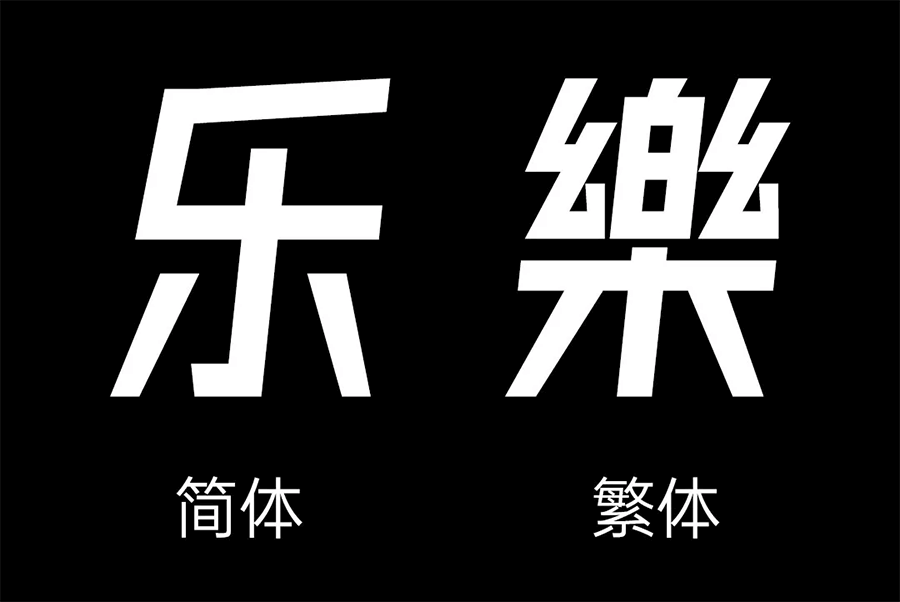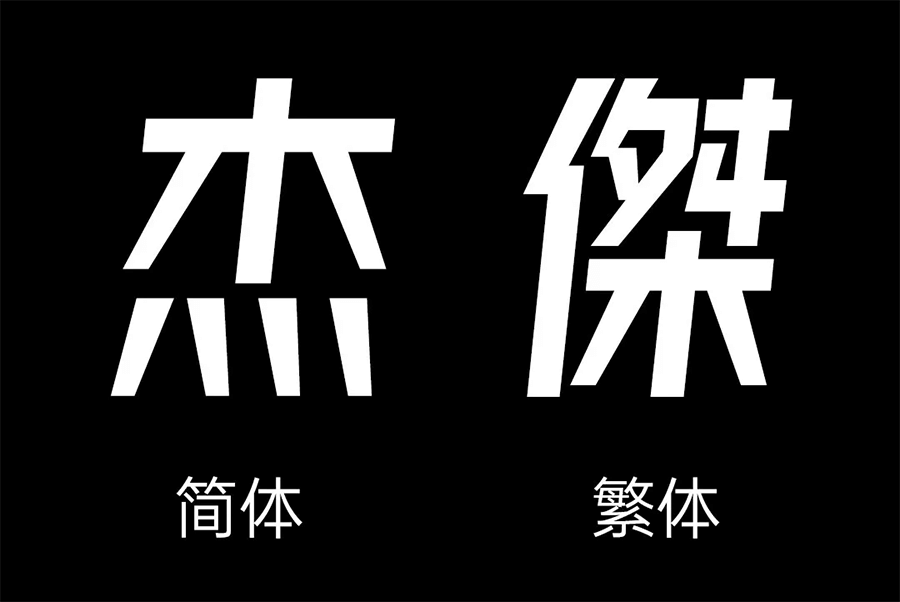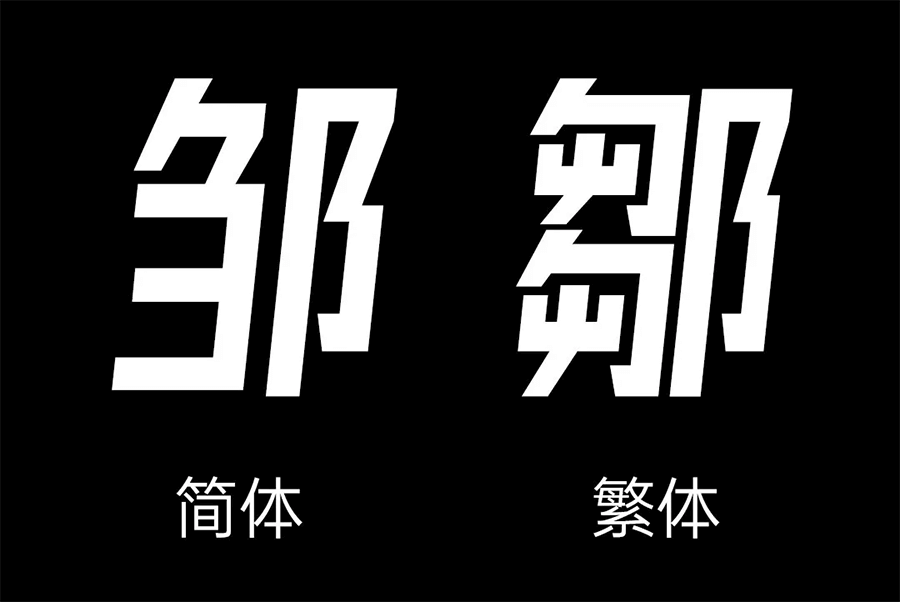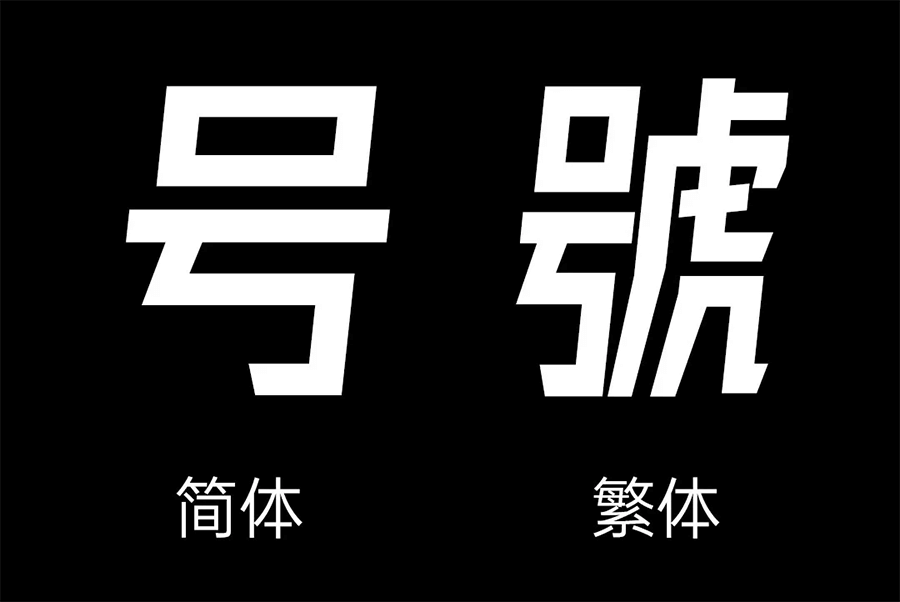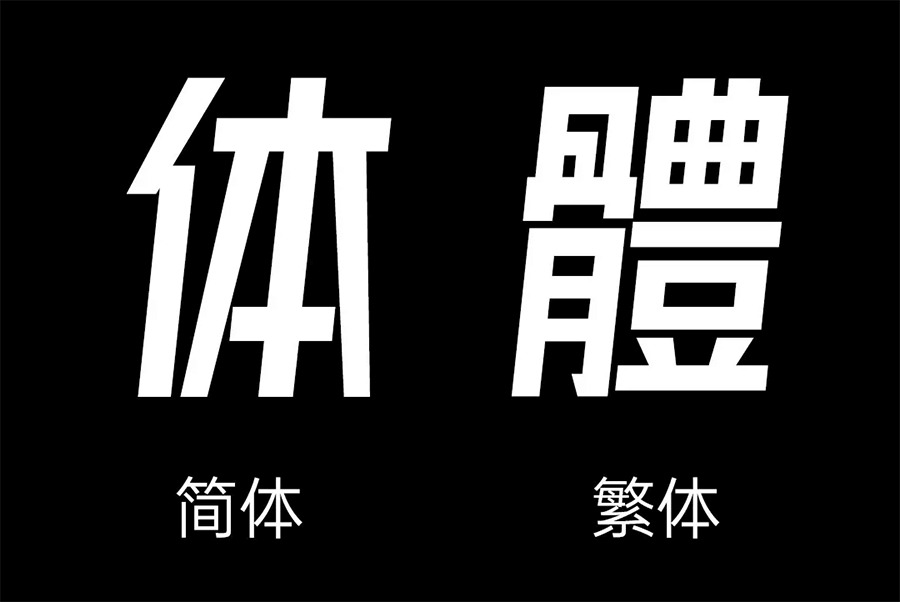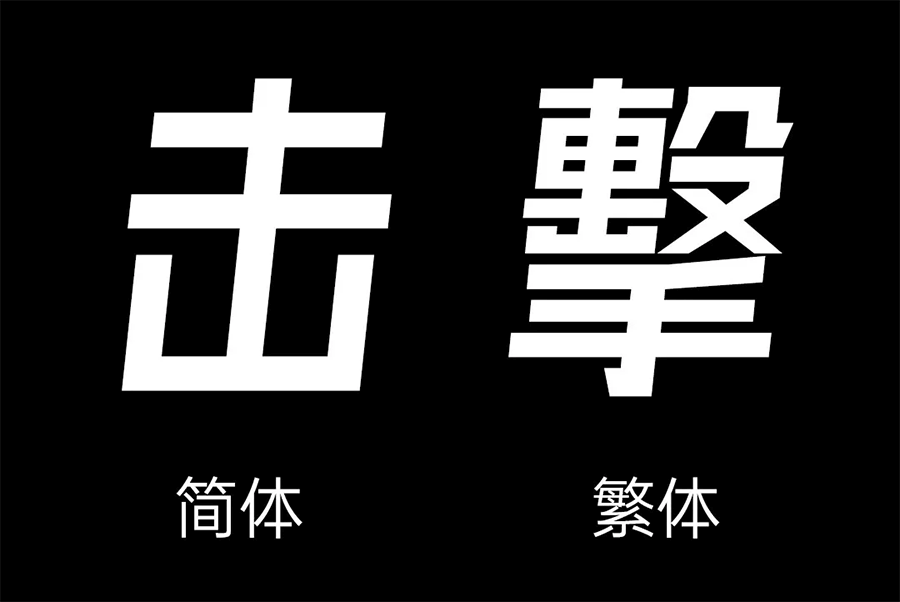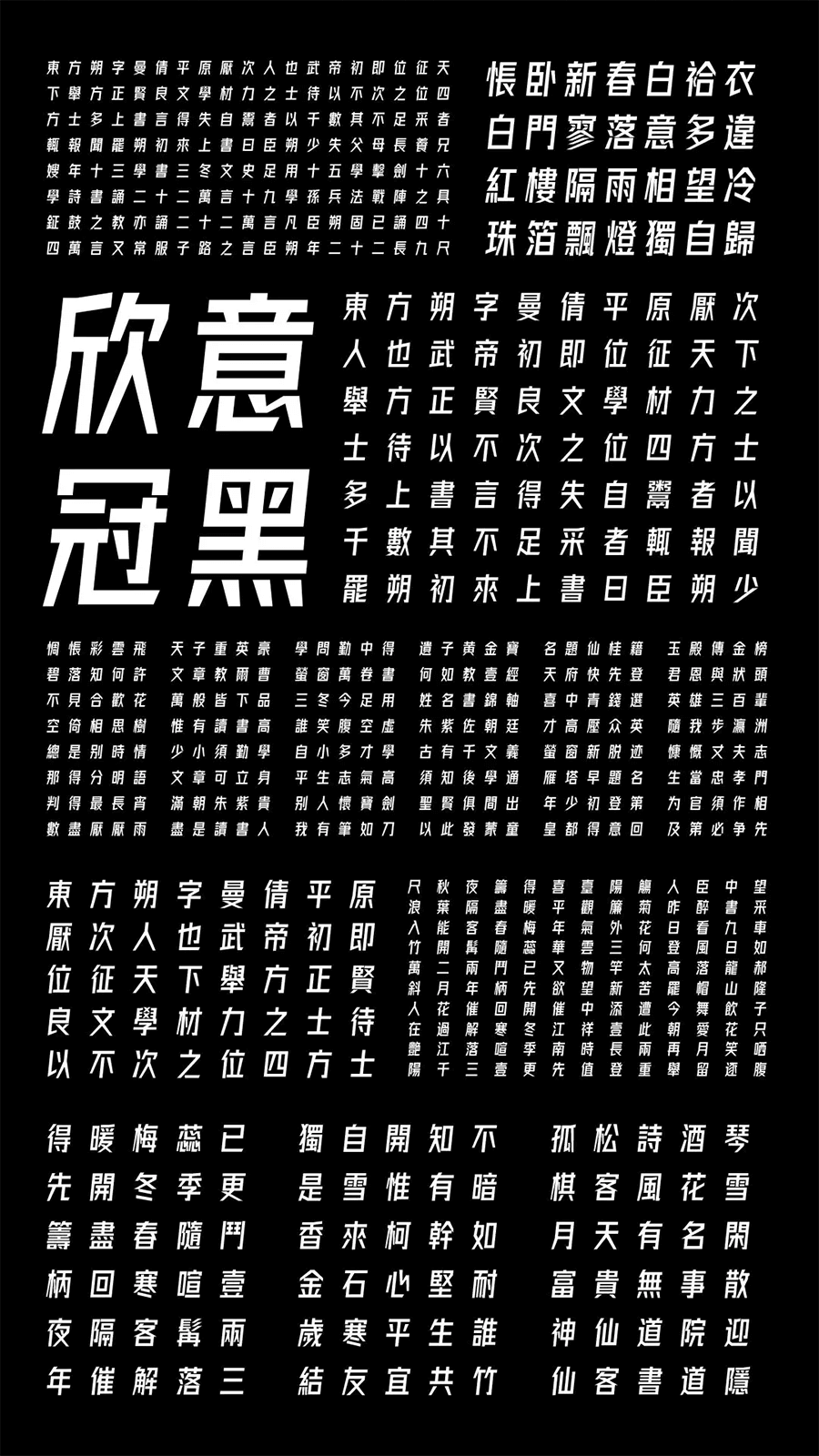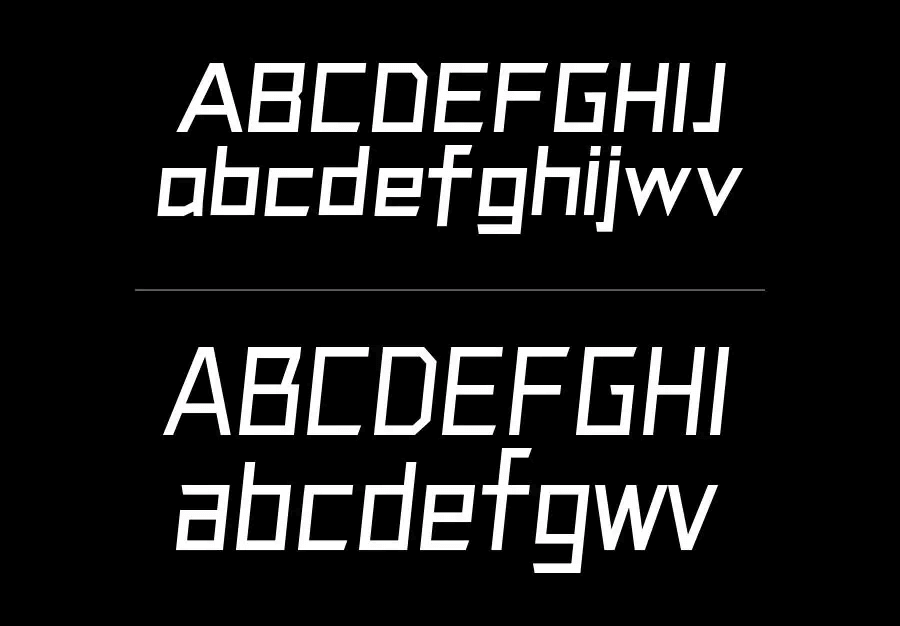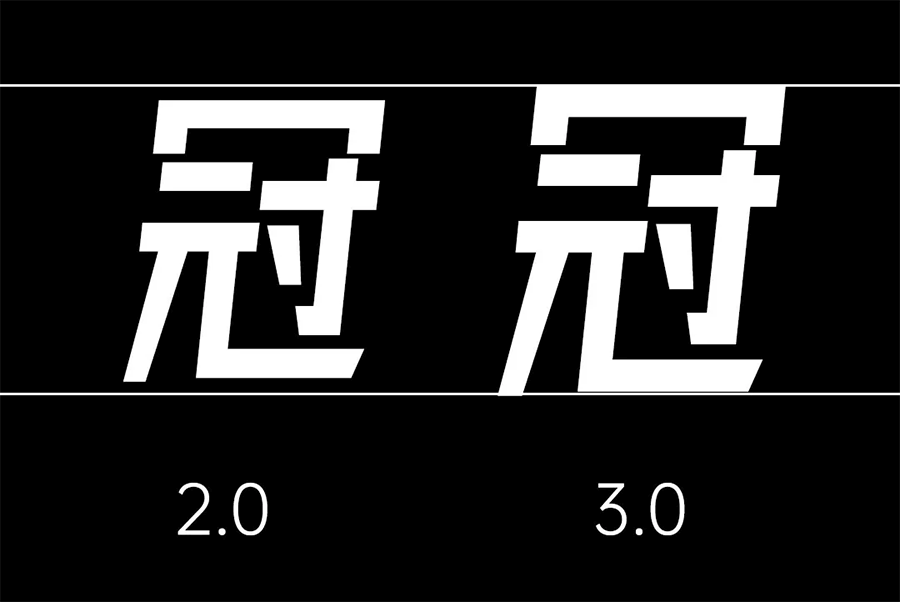
字体圈欣意冠黑体:因为疫情而生的高质量免费商用字体
字体作者:字体圈Design (中国大陆) 字体字重:1个
2020年4月1日字体圈的@邹乐伟正式发布了《字体圈欣意冠黑体》第一版,之后也面临了很多问题,仅半个月就更新了2.0版本,当时夸下海口说不出意外3.0就是繁体版,同时也有不少的朋友反应这个字的各种各样的问题,当然当时也把这些问题都解决了,重心还是在繁体设计上面。但你看完今天的文章,你会惊奇的发现,今天所更新的内容更加实用!
新增汉字约700余字符
新增的汉字主要是对于港澳台地区的国字标准,中文现总涵盖9864字,现在的阶段相对来说比较快了,很多字都有现成的字拿来拼,做起来还是比较轻松的。
新增符号约200余字符
去年有朋友跟我反映过没有序号的问题,现在也补上来了。
调整字母数字符号的字符间距
3.0默认的字母数字符号的字间距过于小了,看上去非常紧凑,而我们的中文却比字母的间距大,所以就重新调整了一下。
至此,关于4.0的更新,已经全部展示完了,我觉得算是一次大更新了,新增了这么多字,不出意外的话,5.0版本应该会做细粗体或者可变体吧。
• 修复沿字没倾斜的问题
• 新增字符“咘”;
• 新增一键呼出繁体字功能
• 更新数字“8”与中文“日”的设计。
• 更新“啾”字符;
• 新增biang字编码u30EDD
• 修改部分字形的细节。
• 更改部分字形设计
• 重新设计西文数字标点部分
• 添加3000+个繁体字符,现在字符数量是将近10000个了
• 还原字形默认大小
• 添加了生僻字“biang”
• 添加了新的汉字字符
• 空格字符宽度减小
• 中文标点调整
• 所有字符调整默认间距
• 字体圈欣意冠黑体发布